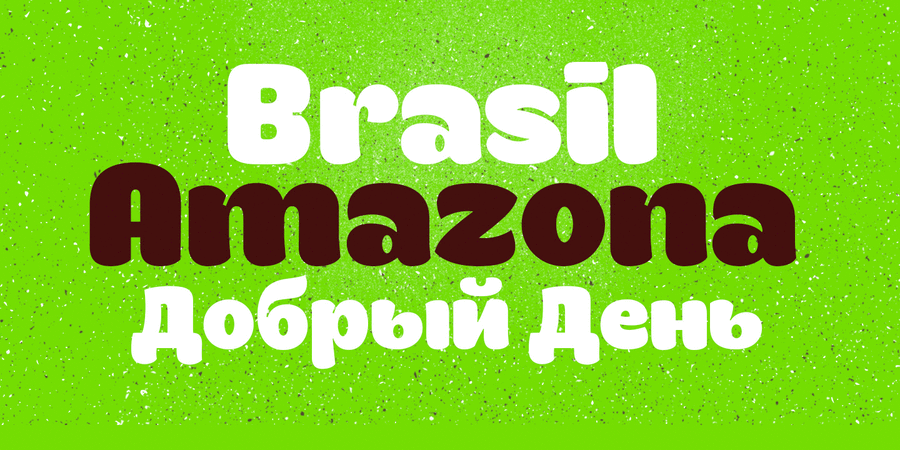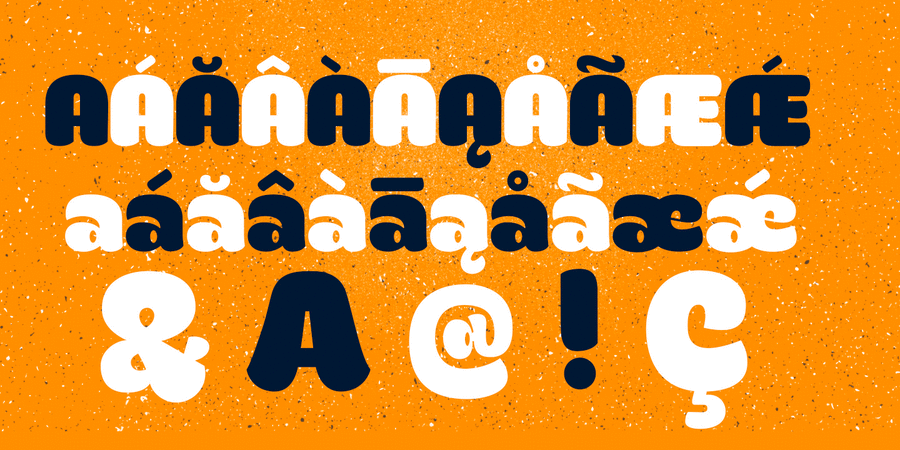
Конга Про – это версия шрифта Конга, разработанного в 2012 году. Обновленная версия включает кириллицу и альтернативные глифы. Шрифт разработан в 2015 году Родриго Арая Салас при участии Андрея Кудрявцева.
Асоціації з сімейством шрифтів Konga ProОсобистість і характер гарнітури:
веселий, задерикуватий, смішний, доброзичливий, добродушний, добрий, радісний, грайливий, привітний, пустотливий, непосидючий, оригінальний, свіжий, стиглий, соковитий, смачний, важкий, помітний, яскравий, дитячий, наївний, карикатурний, милий, мультяшний, дотепний, домашній, літній, М'який, щедрий, пишний, затишний, приємний, живий, гладенький, сімейний, святковий, тісний, товстий, прикольний, няшний, усміхнений, апетитний, солодкий, щасливий, фруктовий, ягідний, рясний, насичений, спекотний
молоко, булочка, десерт, солодощі, торгівля, кондитерська, випічка, булочна, кафе, м'яка іграшка, родина, дитяча книжка, фарби, фарба, школа, табір, гумор, анімація, сніданок, іграшка, дитяче харчування, їжа, закуска, зоопарк, клоун, розфарбування, гра, фаст фуд, зоомагазин, тварини, відпочинок, цирк, мультфільм, дитсадок, дитячий ранок, сік, канікули, торт, шоу, телебачення, морозиво, соус, сметана, кетчуп, жуйка, підгузок, чіпси, фрукти, мармелад, сир, графіка, ілюстрація, дім, ранок, малюк Гарнітура має ознаки стилів: